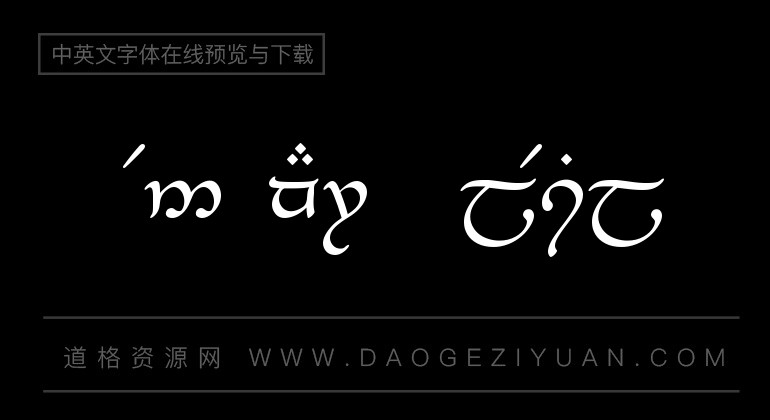
Tengwar Elesil
Tengwar Elesil字体是一款由Tengwar字体设计师David K. Stokes创作的Tengwar字体,它是一款全新的Tengwar字体,可用于创作新的Tengwar文字。Tengwar Elesil字体的设计重点在于结合了Tengwar字体中的传统元素和现代技术,以及更多的细节,从而使Tengwar Elesil拥有更加完美的外观和更加准确的字形。Tengwar Elesil字体的特点是具有更多的字形,更多的细节,以及更加精致的外观,使其能够更好地表达Tengwar文字的精髓。
Tengwar Elesil是一款非常不错的手写艺术字体,具有很好的视觉感,适合于文化类的宣传设计、商业类品牌的广告和产品包装设计以及个性化文字排版等较多场景。